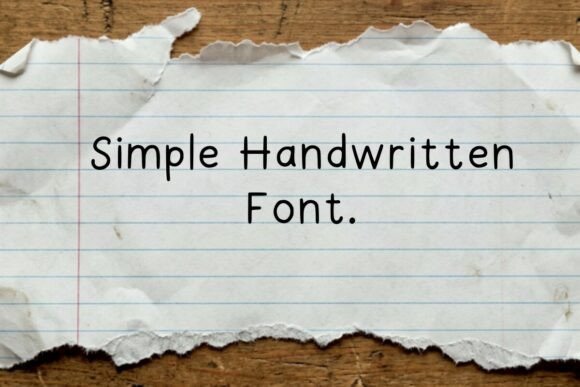
Simple Handwritten
Simple Handwritten – Une police manuscrite chaleureuse et professionnelle
Découvrez Simple Handwritten, la police qui capture l’essence même d’une écriture à la main naturelle et fluide. Avec ses traits monoline, ses terminaisons arrondies et son apparence scolaire soignée, elle apporte une touche de proximité tout en restant lisible et élégante.
Pourquoi choisir Simple Handwritten ?
- Style authentique : imite parfaitement le tracé d’un stylo sur du papier.
- Lisibilité optimale : idéale pour les longs blocs de texte et les petites tailles.
- Polyvalence d’usage : convient aux ressources éducatives, aux journaux numériques, aux notes personnelles et aux visuels sociaux.
- Sentiment de fait main : ajoute une dimension humaine et chaleureuse à chaque projet.
Utilisations idéales de Simple Handwritten
- En-têtes de blogs confortables et accueillants.
- Fiches d’exercices et supports pédagogiques pour enseignants.
- Journaling numérique ou agendas personnalisés.
- Graphiques pour réseaux sociaux visant à créer un lien émotionnel avec l’audience.
- Cartes de vœux, invitations et tout projet nécessitant une touche personnelle.